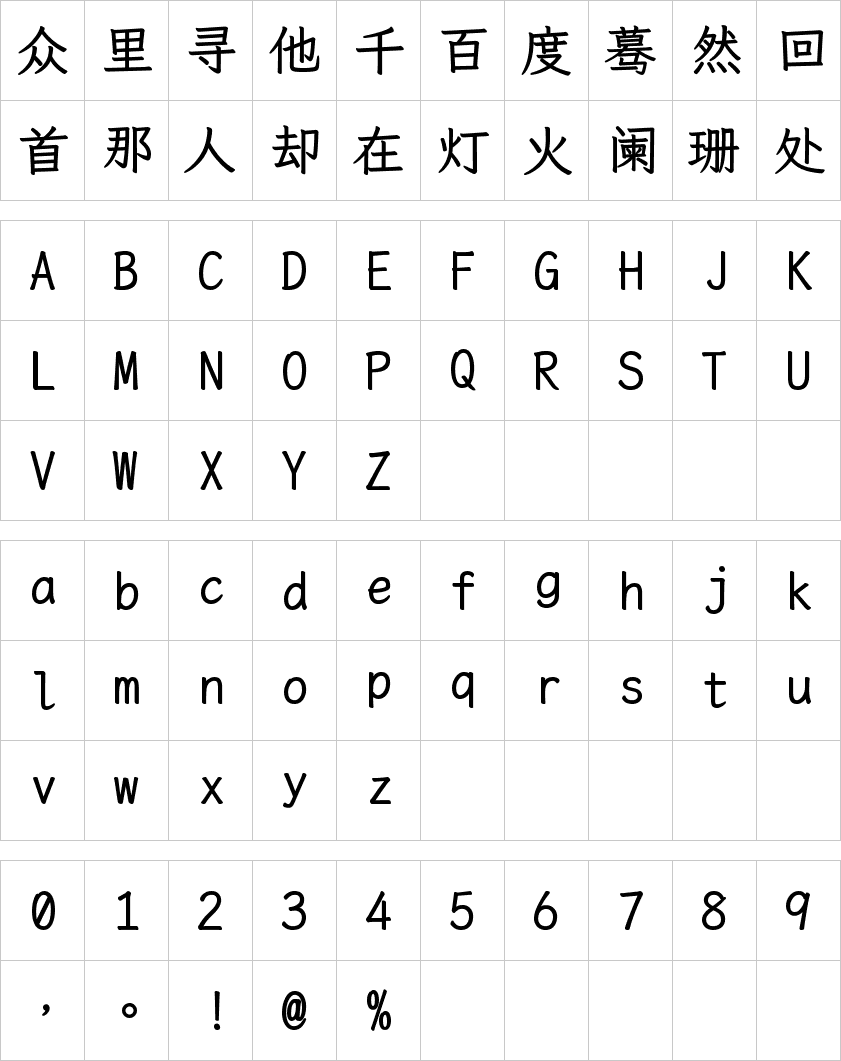
霞鹜文楷等宽
2020 年 12 月,日本著名字体厂商 FONTWORKS 在 GitHub 上发布了 7 款日文字体,分别为 Train、Klee、Stick、Rock-n-Roll、Reggae、Rampart 和 DotGothic16,根据 SIL Open Font License 1.1 授权许可开源。7 款开源日文字体各有各的特点,而这 7 款字体中,字符数量最多的是 Klee。
这是一款有着日本教科书体风格的字体,兼有仿宋和楷体的特点。一些 DIY 字体爱好者曾先后用仿宋等字体补全这款字体,作为手机系统的美化字体移植在 iOS、Android 等手机系统中,受到很多玩机发烧友的欢迎。不过这样补全的字体有一些不足之处。 第一,原有字体和后补字体之间有着一定的差异,致使一些不同的文字(如 Klee 原有汉字与后补简体字)混排之后会有一定的违和感。 第二,由于补字所用的字体为商业版权字体,补全之后不可用于商业用途,还会有侵权的风险。此外,目前现有的开源中文字库里,楷体类寥寥无几,仿宋类则几乎没有。
鉴于此,也为了丰富开源中文字体中的楷体门类,2021 年 1 月 20 日起,本人开始了为 Klee One 这一高质量的日文开源字体补全简繁常用字的尝试。因该字体具有一定的「文艺气息」,命名 「霞鹜文楷」(其实当初是感觉这款字体适合正文阅读定名「文楷」,后来发现这款字体可能并不太适合大段正文排版,相比之下更加适合诗词之类的中等长度文本排版,或者注释排版)。由于 Klee One 字体的 Regular 字重太细不太适合阅读,选取原字体 SemiBold 字重作为 Regular 字重。经过长时间的积累,目前已发展成简繁日韩均支持的 3 字重字体家族 (虽然拙劣粗糙了点) 。